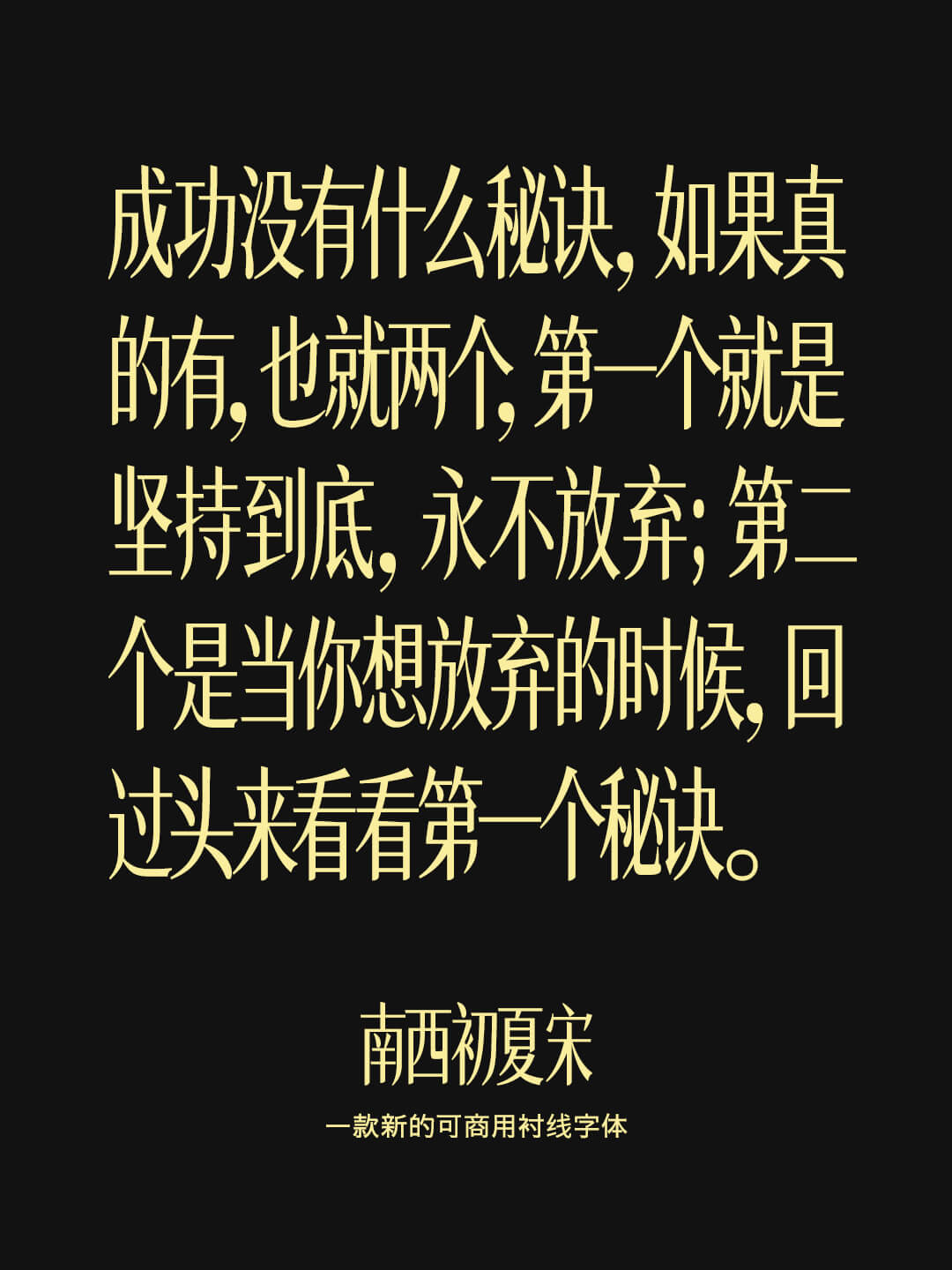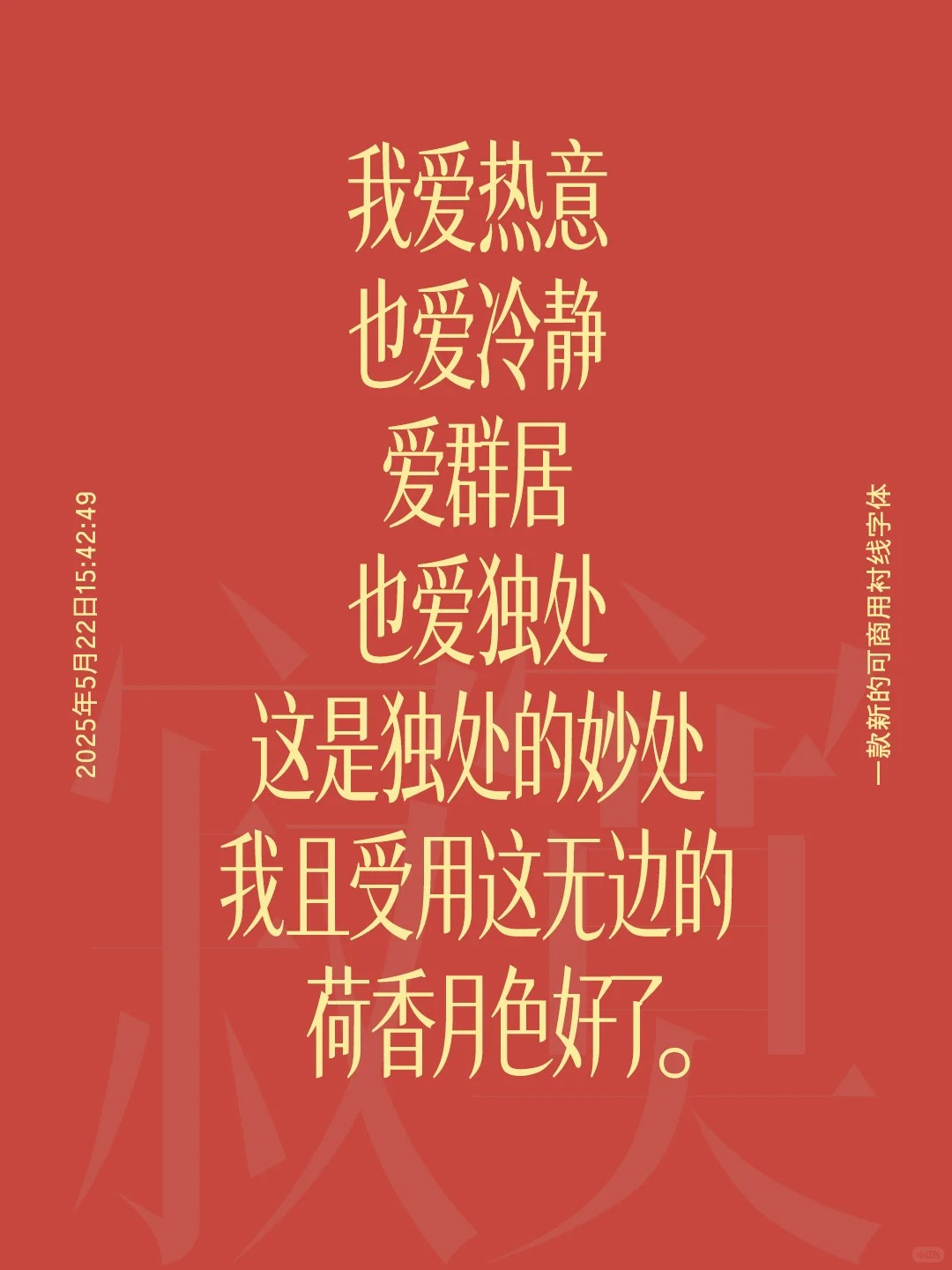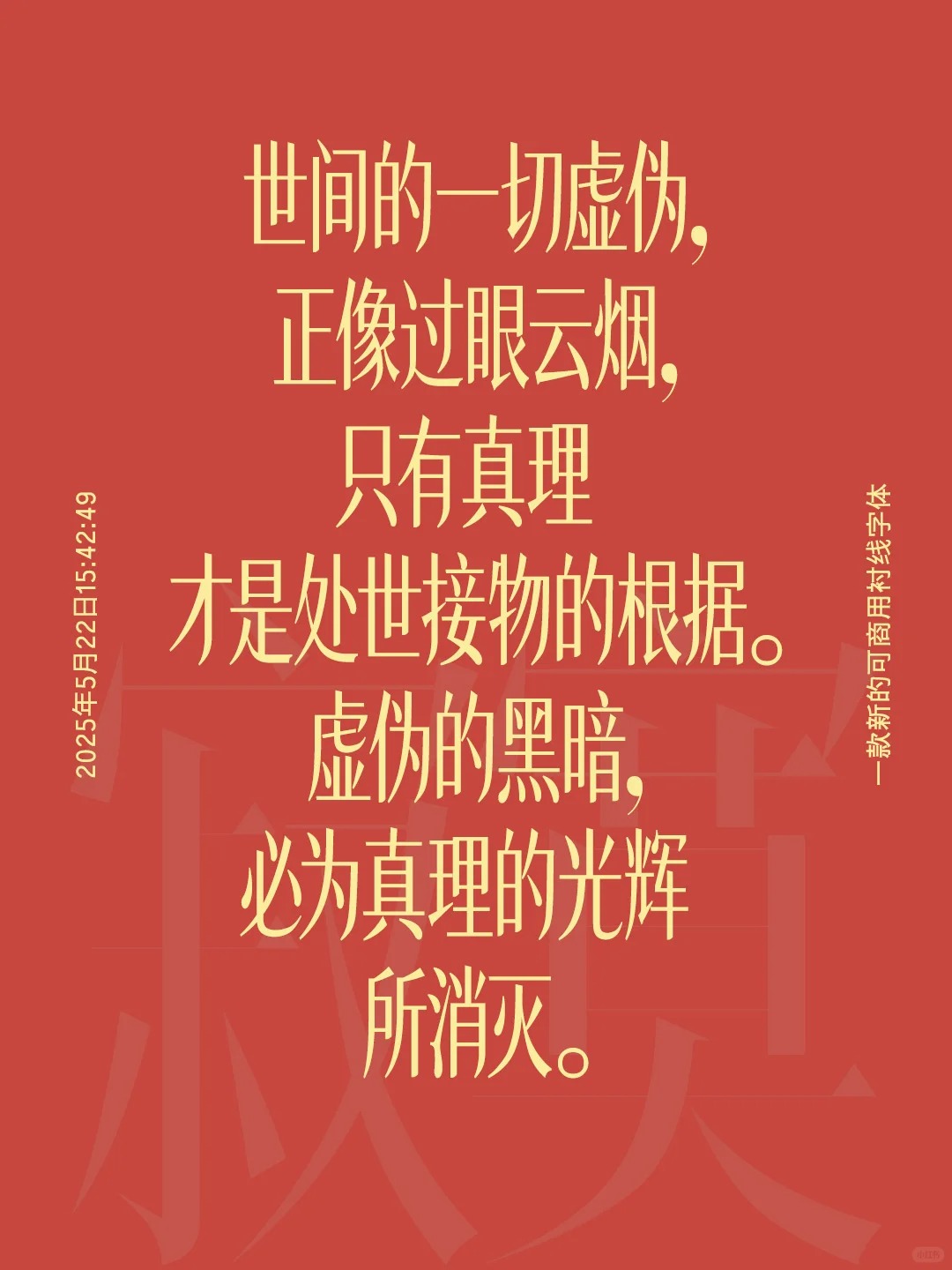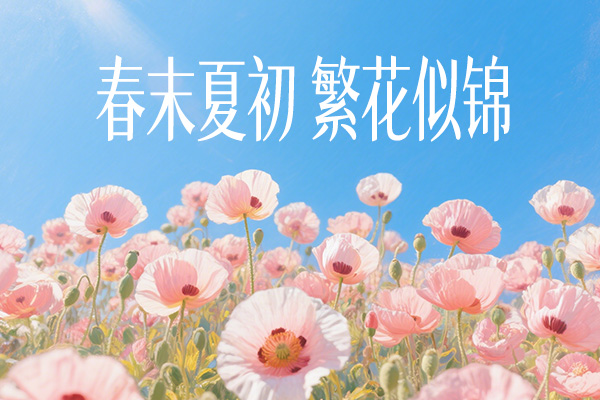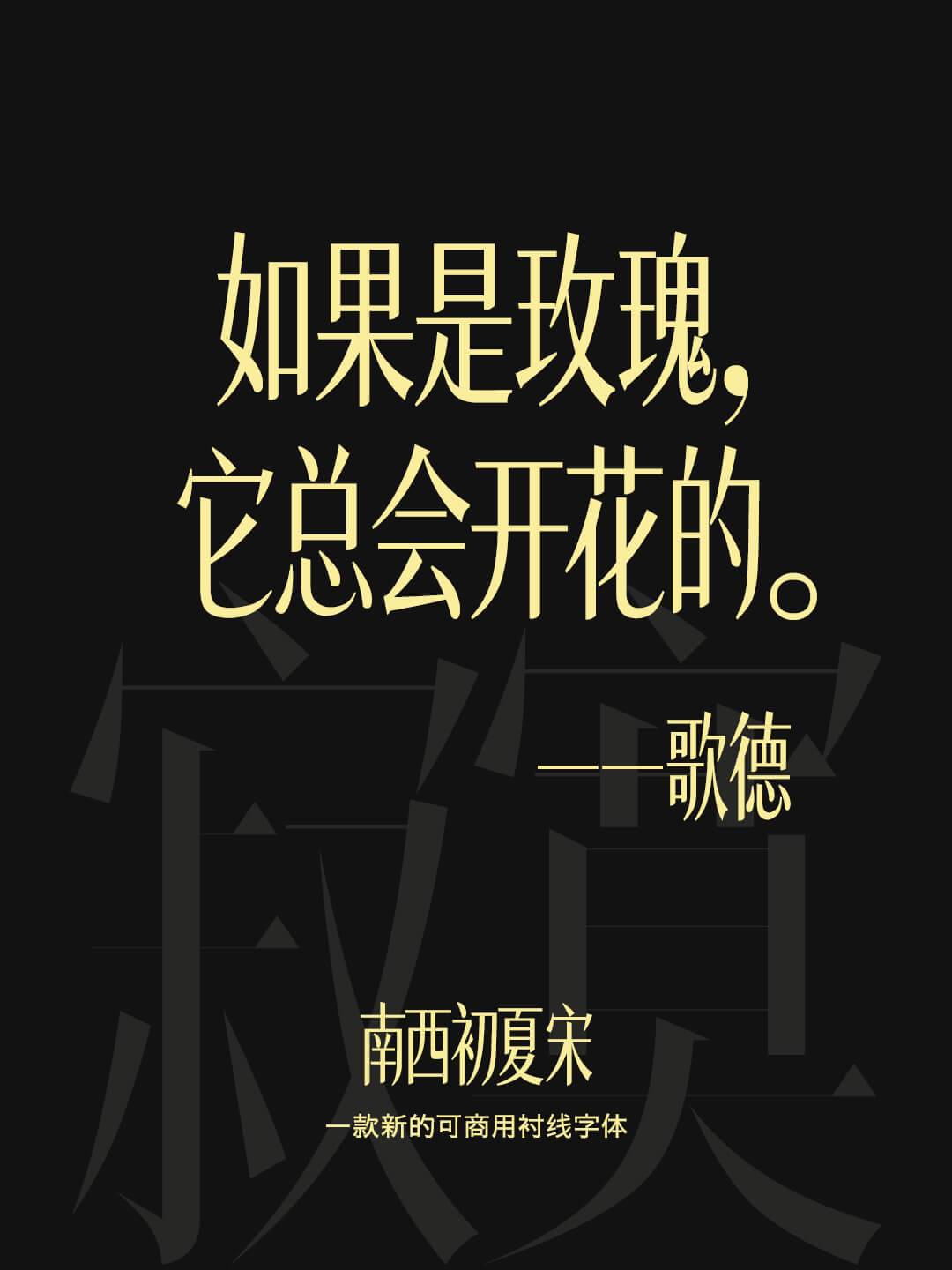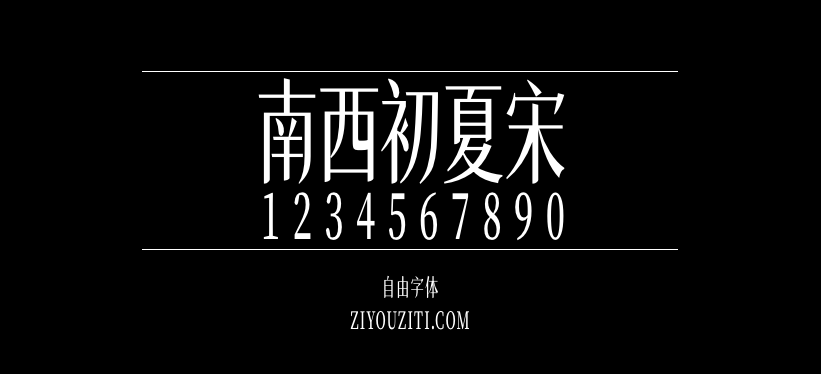
南西初夏宋
南西初夏宋是江苏的设计师@松陵南西基于思源宋体制作的一款可商用衬线字体。这款字体以思源宋体为基底,在细节处融入了独特的设计巧思。横笔末端微微上扬的弧度。字体的收笔,既保留了宋体原有的端庄典雅,又为文字注入了一丝手写般的灵动与温度。
南西初夏宋基于思源宋体创作,而思源宋体的字符集是很全面的,简体繁体基本都不会缺字,实测GB2312规定的6763字是都全的。